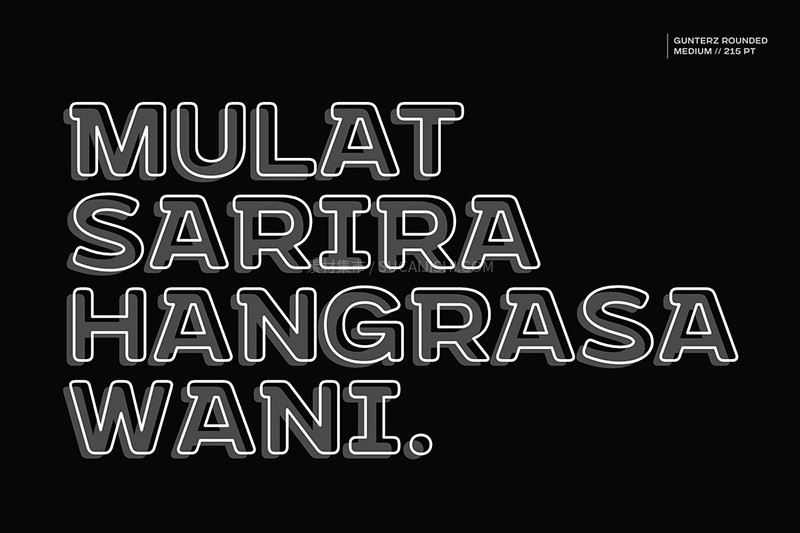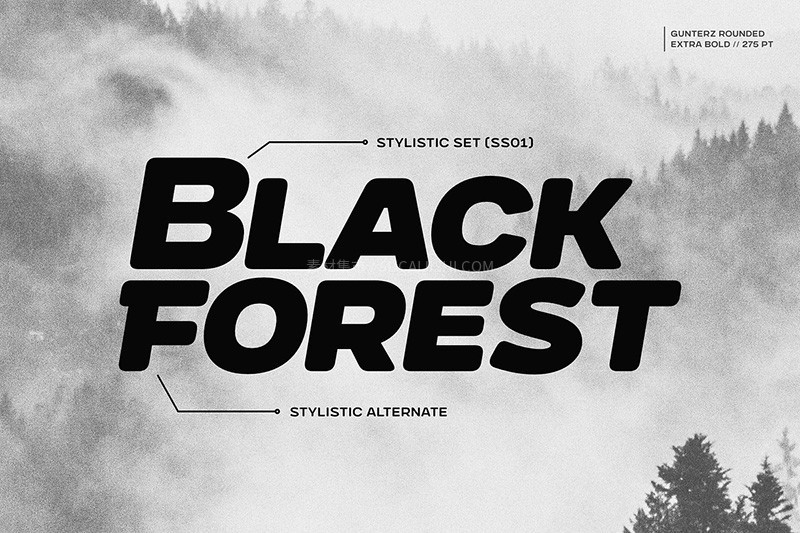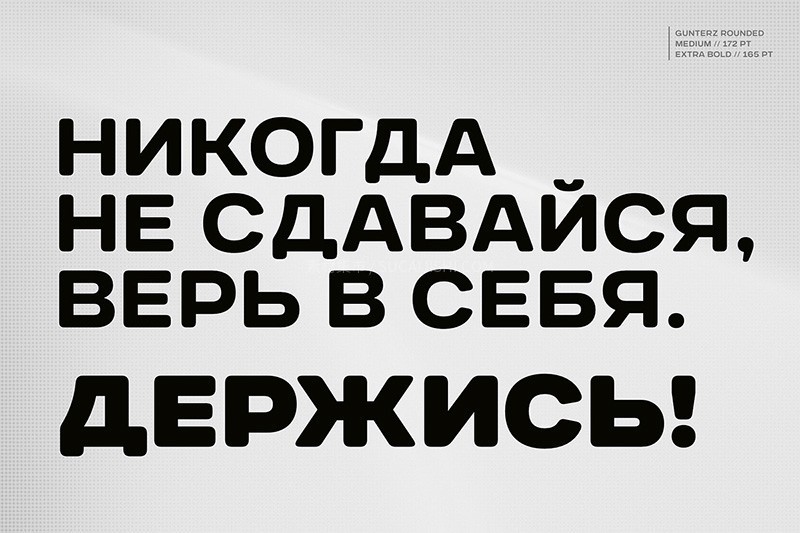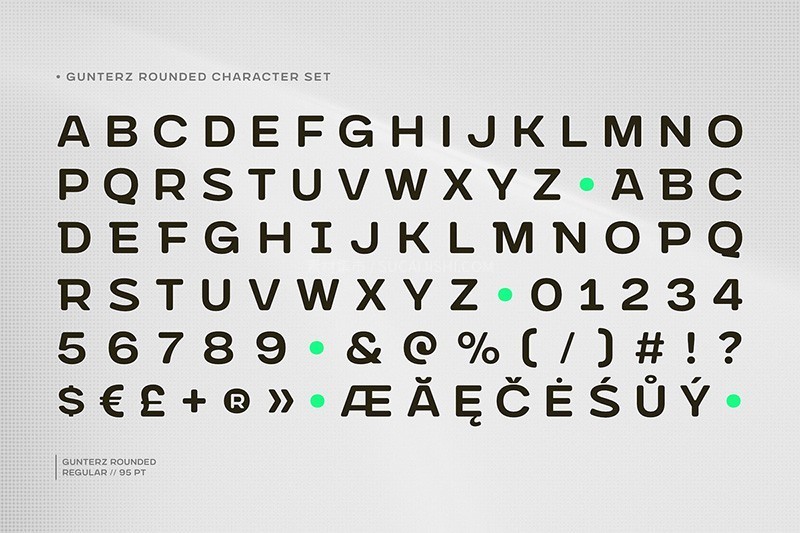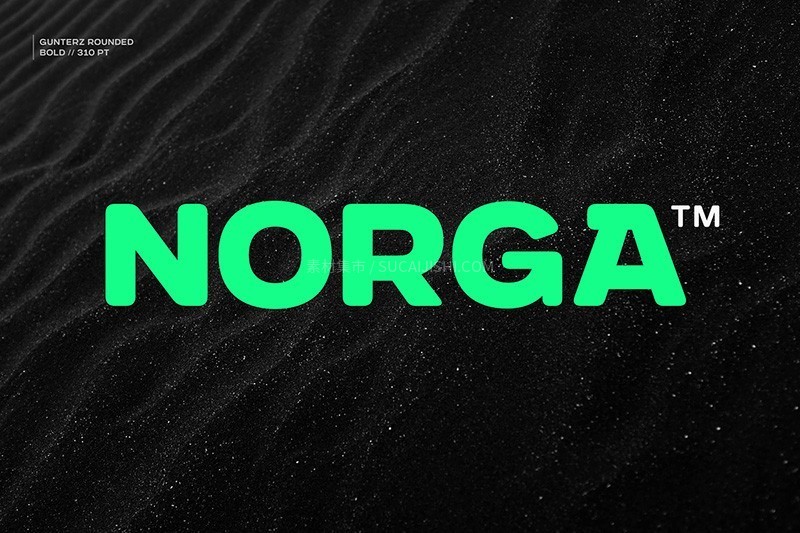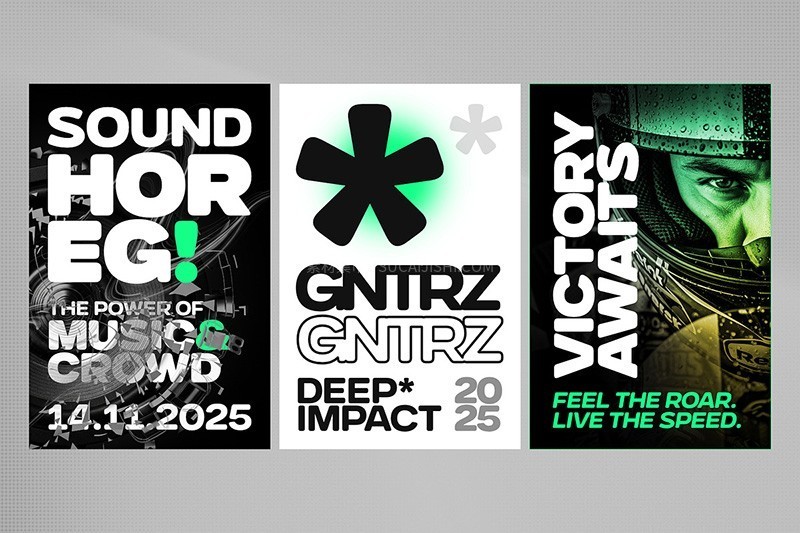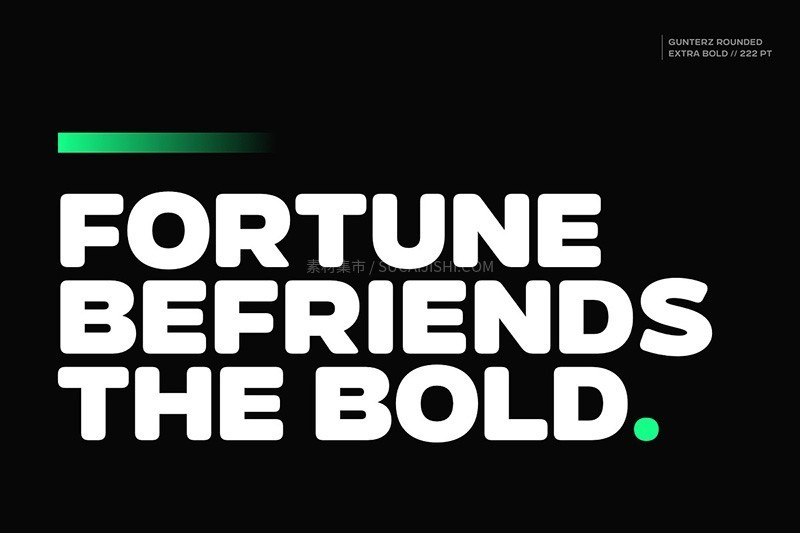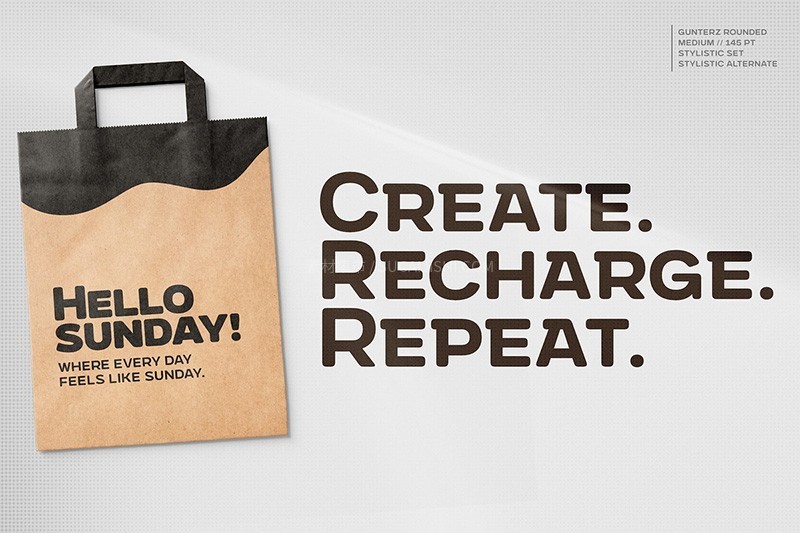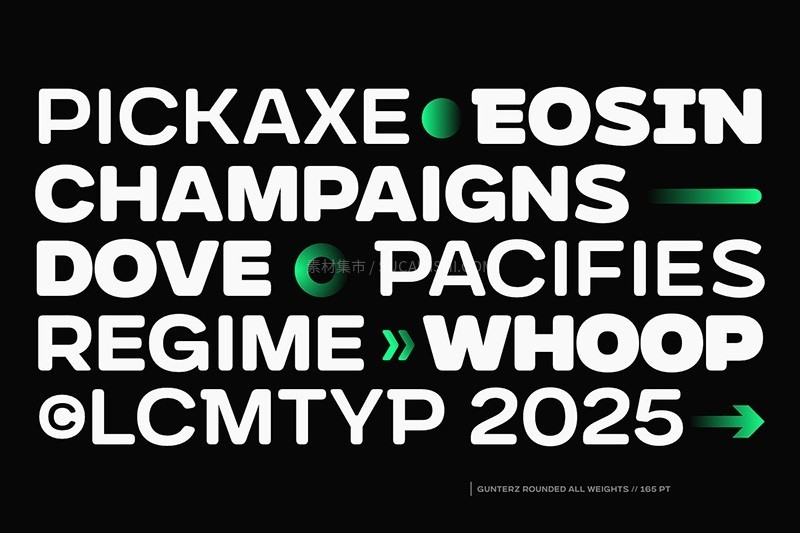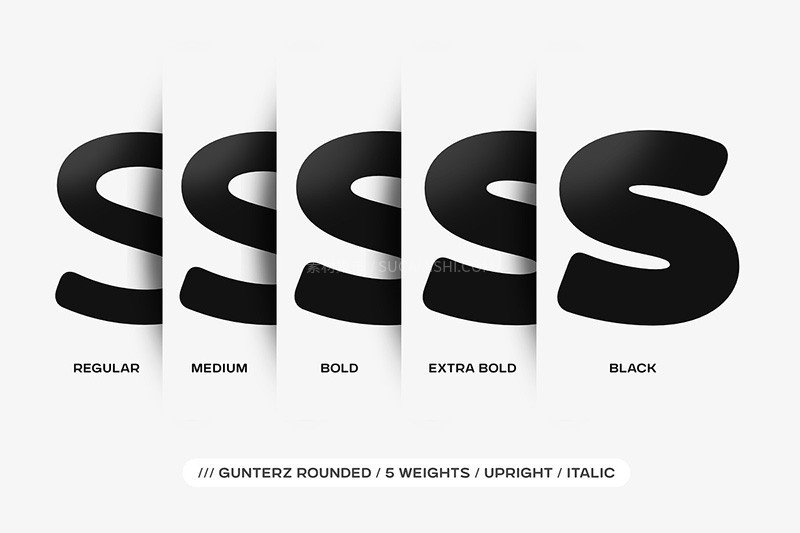
Gunterz Rounded 时尚粗圆英文字体
Gunterz Rounded 是字体 Gunterz 的圆角版,它保留了原版字体的强劲气势,并以柔和圆润的边角增添了亲切感。它拥有五种字重,并配有斜体和多种 OpenType 功能,非常适合需要强劲而又兼具魅力的设计。适用海报标题、徽标设计、产品包装、品牌宣传、数字内容、网页设计等。